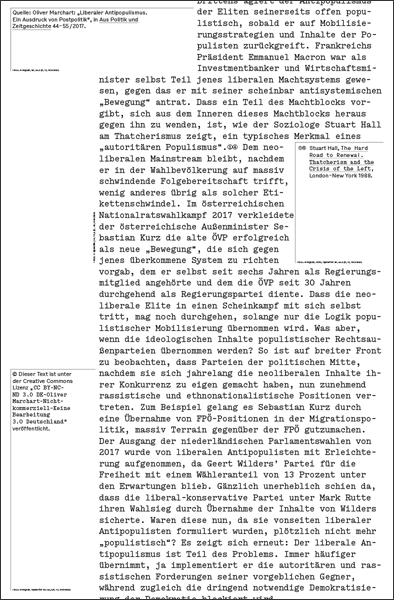
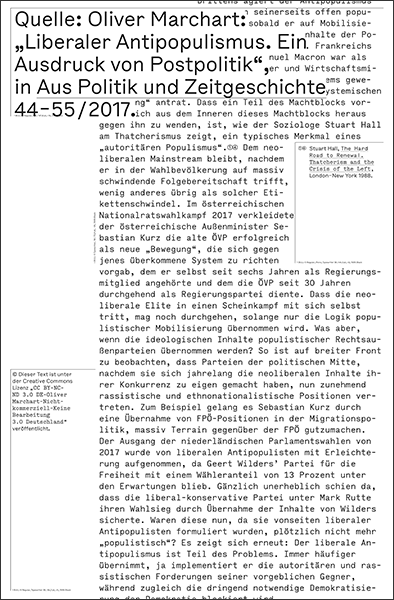
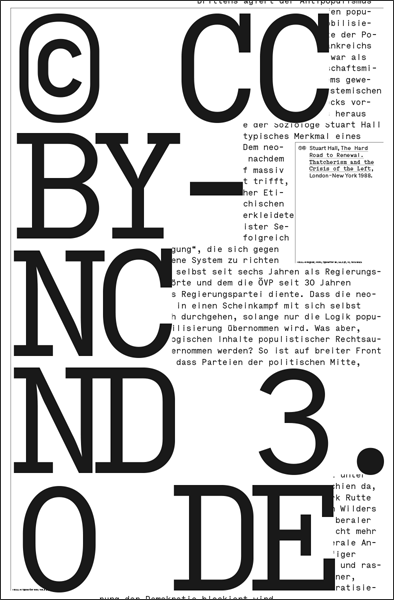
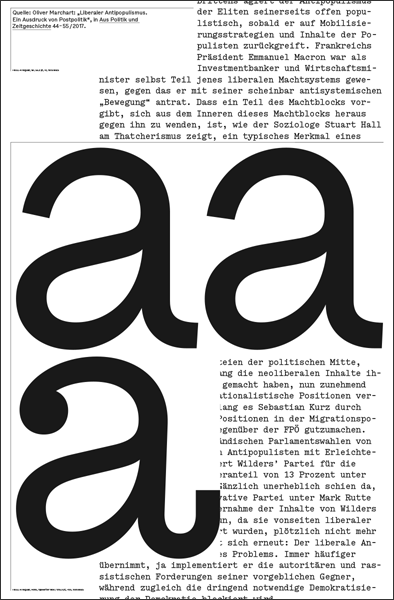
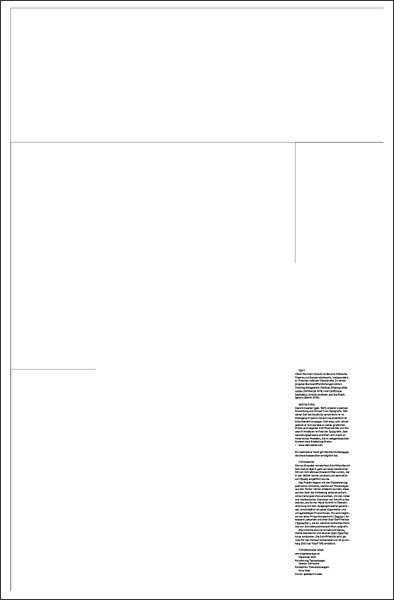
Text
Gestaltung
David Einwaller (geb. 1991) arbeitet zwischen Anwendung und Entwurf von Typografie. Seit seiner Zeit bei Studio Es verwirklicht er im Alleingang Projekte die sich hauptsächlich im Kulturbereich bewegen. Seit etwa acht Jahren widmet er sich parallel zu seiner grafischen Praxis auch eigenen Schriftentwürfen und Research-Ansätzen im Feld der Typografie. Sein Gestaltungsprozess orientiert sich meist an historischen Modellen, die im zeitgenössischen Kontext neue Bedeutung finden. www.deinwaller.com [Ein besonderer Dank gilt Martha Stutteregger, die diese Kooperation ermöglicht hat.]
Typografie
Die von Einwaller entworfene Schriftfamilie mit dem Namen Bull-5 geht auf einen bestimmten Stil von Schreibmaschinenschriften zurück, der in den 1960er Jahren entstand und vermutlich von Olivetti eingeführt wurde. Das Projekt begann mit der Digitalisierung gedruckter Etiketten, welche auf Fotoabzügen aus den 1980er Jahren entdeckt wurden, diese wurden über die Schließung eines amerikanischen Zeitungsarchivs erworben. Um den rohen und mechanischen Charakter der Schrift zu bewahren, wurde der Mono-Schnitt in Übereinstimmung mit dem Ausgangsmaterial gezeichnet, einschließlich all seiner Eigenheiten und unregelmäßigen Proportionen. Sie wird begleitet von einer Proportionalschrift (Regular) für bessere Lesbarkeit und einer Slab-Serif Version (Typewriter), die ein weiteres ikonisches Merkmal von Schreibmaschinenschriften aufgreift.